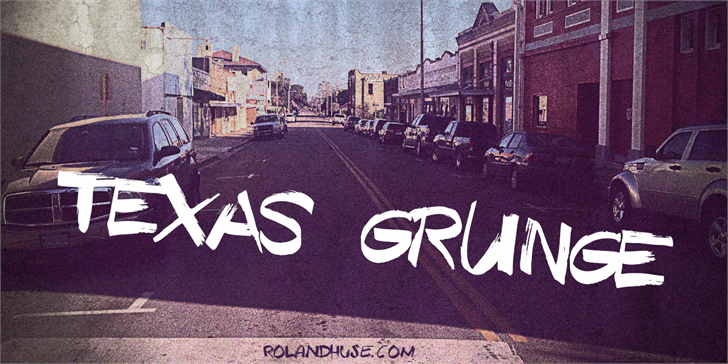
A Texas Grunge font é uma escolha perfeita para aqueles que buscam trazer uma cara única e vibrante a seus designs digitais. A designer Hamilton criou esta fonte, com ênfase no estilo script e grunge, permitindo que os designers explorem suas variações alternativas de letras maiúsculas e minúsculas. Esta característica especial permite que os artistas textuais criem fluxos interessantes e personalizados para qualquer tipo de projeto. Com sua aparição casual e autêntica, a Texas Grunge traz uma sensação de originalidade e energia à sua obra final. Seja você um designer gráfico, um escritor ou até mesmo um blogueiro digital, esta fonte oferece inúmeras possibilidades criativas para tornar seu trabalho ainda mais único e vibrante.